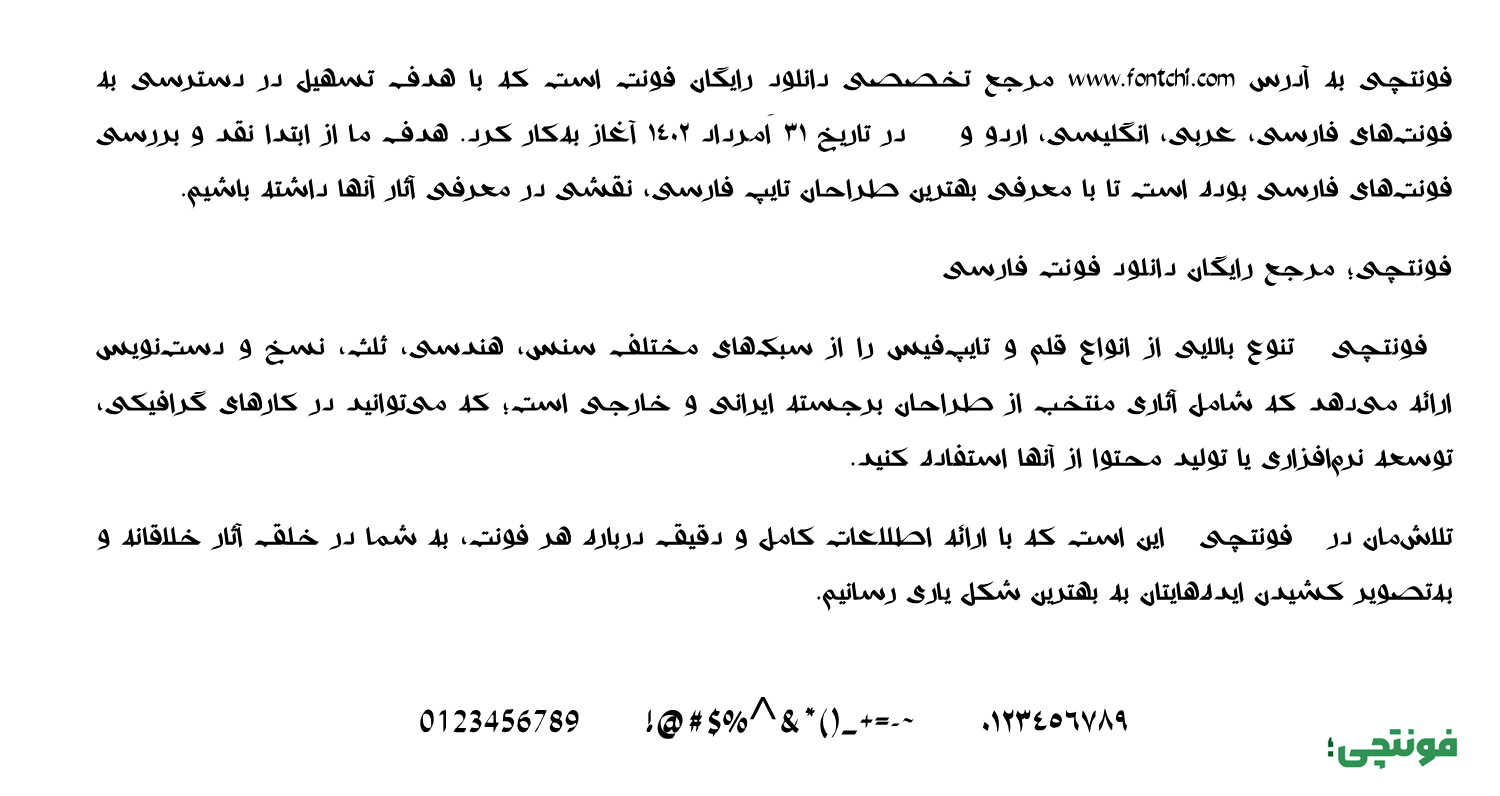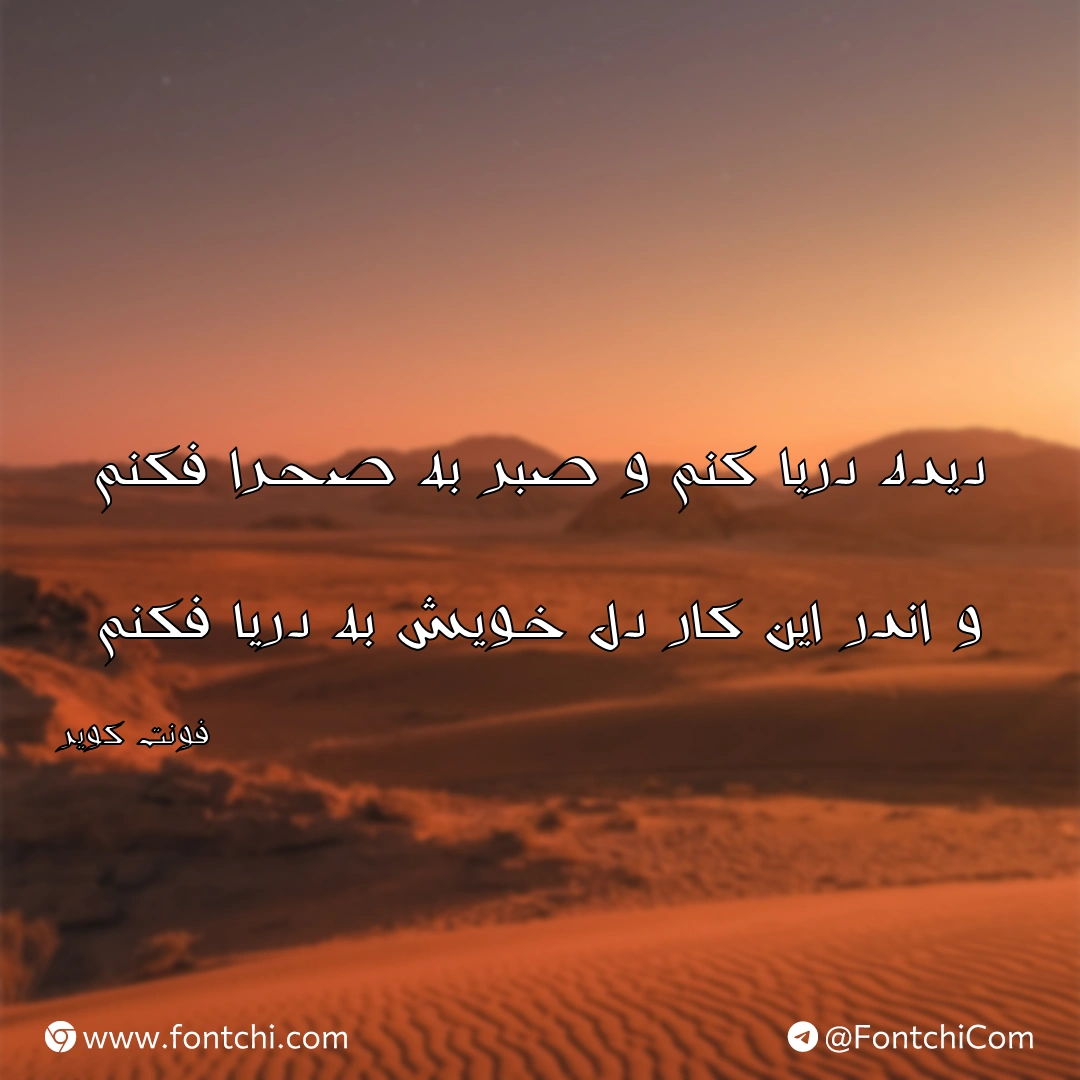
فونت کویر (A Kavir)
فونت کویر (به انگلیسی: A Kavir) از دیگر فونتهای آزاد فارسی است که به سبک هندسی طراحی شده است. اما هندسه بهکار رفته در این قلم بهگونهای است که آن را به یک فونت خطاطی شبیه کرده است. در ادامه با دانلود فونت کویر رایگان همراه شما هستیم.
فونت کویر درواقع یک قلم عربی بوده است که با توجه به تفاوتهایی که در حروف عربی «ک، ی، ه، ؤ، ئ» وجود دارد، برای زبان فارسی قابل استفاده نبود. از همینرو علی سواری یک نسخه برگردان از فونت مذکور را که دارای گلیفهای کامل حروف فارسی است با نام کویر منتشر نمود.
فونت کویر از زبان فارسی و عربی پشتیبانی نسبتا کاملی دارد. کلیه حروف دارای ظاهری هندسی هستند که آن را به یک فونت خطاطی شبیه کرده است. چشمیها در برخی حروف مانند «ص، ض، ط، ظ» دارای ابعاد بزرگ هستند، اما در مقابل در برخی حروف دیگر مانند «م، ه، ق، ف» دارای ابعاد کوچکتری هستند.
این فونت همچنین از همان سبک نزدیک برای زبان انگلیسی برخوردار است. در نتیجه میتوانید برای پروژههایی که چندزبانه هستند از این قلم استفاده کنید تا ساختاری یکپارچه به متن شما بدهد.
فونت Kavir از یک وزن معمولی Regular بهره میبرد که ضخامت حروف به دو بخش تقسیم شده است. بخش اول برای حروفی است که دارای خطوط مورب یا زوایا هستند که دارای ضخامت معمولی و بیشتر هستند. بخش دیگر مربوط به انتهای حروف است که معمولا در حروف کشیده یا خطوط مورب استفاده شده و رفتهرفته از ضخامت فونت کاسته میشود. همچنین تا حدودی در انتهای آن زاویه کج شده است. گویی که حروف دارای دم هستند.
از فونت کویر میتوانید برای پروژههای تزئینی و نمایشی مانند کارهای گرافیکی استفاده کنید. با توجه به اینکه فونت ساختاری هستندسی دارد و برای استفاده در متون بلند خوانایی لازم را نخواهد داشت، توصیه میشود از این قلم فقط با هدف استفاده در عناوین و متون کوتاه استفاده کنید. خصوصا اینکه برای اندازههای بزرگ خود را به خوبی نشان میدهد. از این قلم میتوانید به عنوان فونت جلد کتاب نیز استفاده کنید.